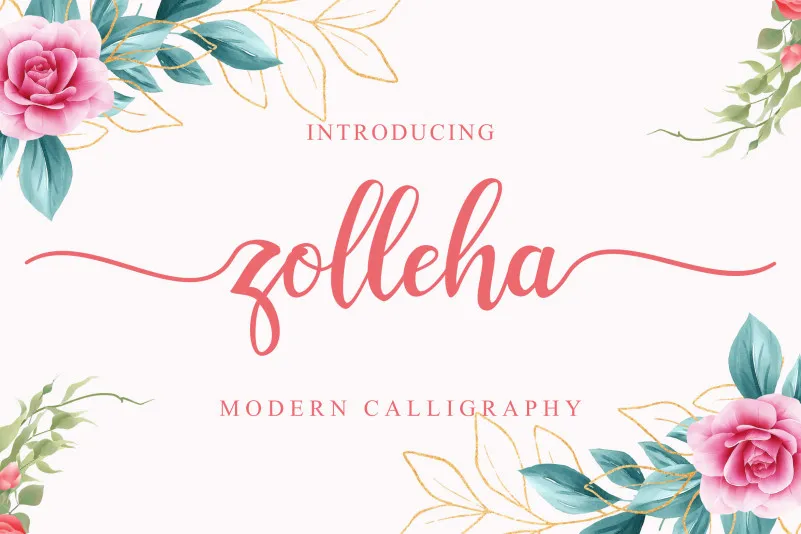
Zolleha Script Font – Download Grátis
Zolleha Script Font é uma fonte cursiva que transmite uma sensação encantadora e elegante ao mesmo tempo. Esta exquisiteira tipografia é uma homenagem sofisticada à antiga calligrafia, mantendo a essência dos traços leves e fluidos do original. Zolleha Script é repleta de alternativas estonteantes que permitem criar designs com um toque especial, seja para as marcas, subtítulos, projetos de casamento ou convites, assinaturas, logotipos, etiquetas, e muito mais. É uma fonte perfeita para aqueles buscando algo sofisticado e divertido, que eleva qualquer projeto ao nível superior sem esforço. Com Zolleha Script, você transformará seus projetos em verdadeiros trabalhos de arte.